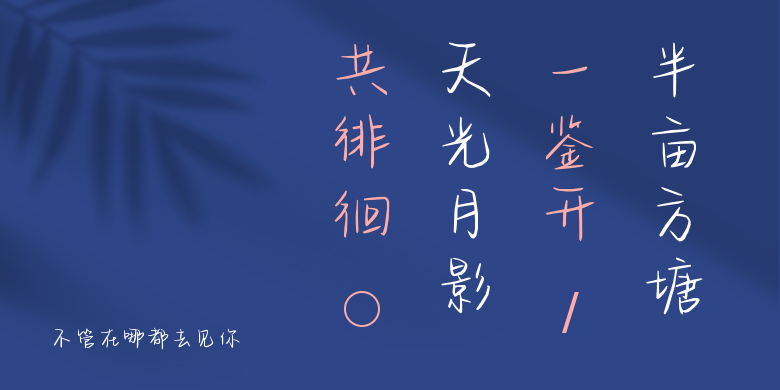
不管在哪都去见你
不管在哪都去见你,这款字体结构工整、笔画清晰,兼顾美观与易读性,适用于标题、正文、海报、包装、LOGO 等多种场景。字形优雅稳定,风格百搭耐看,适配日常排版与创意设计,让文字呈现更舒适、更具质感。不管在哪都去见你一笔一画,皆是细节,以均衡的比例、流畅的线条打造舒适视觉体验,字形端正大气,风格简约现代。无论是商业设计、品牌宣传还是日常排版,都能轻松驾驭,让文字更有格调与力量。不管在哪都去见你字体下载。